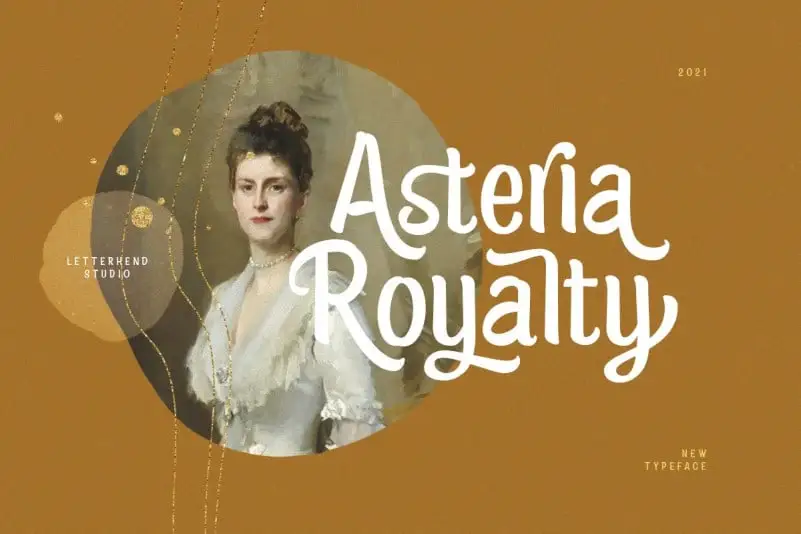
Asteria Royalty Display Font – Fonte Grátis
Asteria Royalty Display Font
Asteria Royalty é uma fonte de exibição criada por Letterhend Studio inspirada nas escritas manuscritas dos cidadãos comuns. Esta fonte foi projetada para capturar a naturalidade e autenticidade que encontramos no estilo do papel químico ou em um caderno de anotações, uma característica que torna-a ideal para uma variedade de aplicações formais. Suas linhas leves e sua disposição única fazem dela uma escolha perfeita para criar identidades visuais atraentes para cartões de convite, logomarcas, revistas, livros, cartões de presente ou mesmo embalagens de moda. Com seu design cuidadosamente elaborado, Asteria Royalty Display Font é uma opção excepcional tanto para projetos formais quanto para aqueles que buscam uma aparência mais pessoal e elegante. Seja qual for o seu propósito editorial ou publicitário, esta fonte irá certamente se destacar em qualquer projeto gráfico.